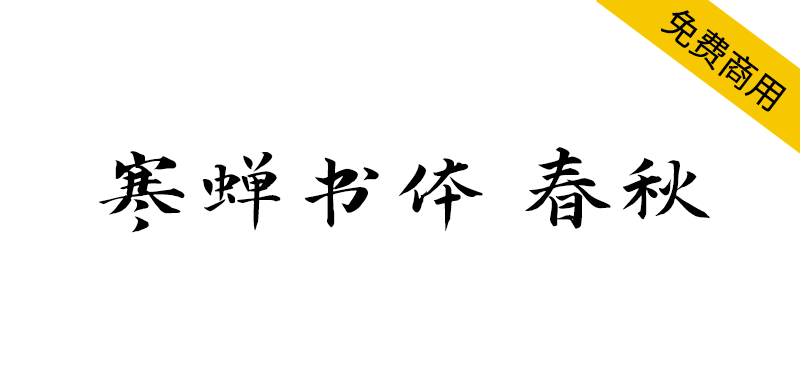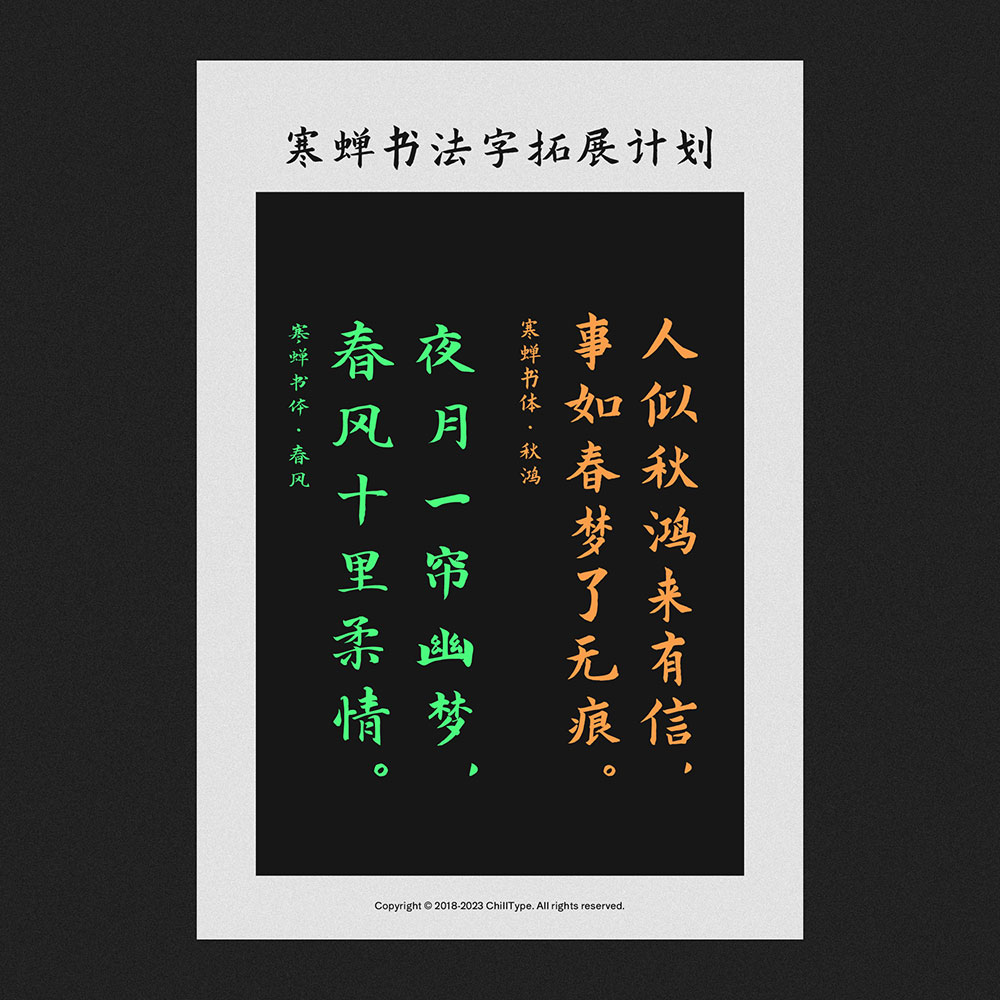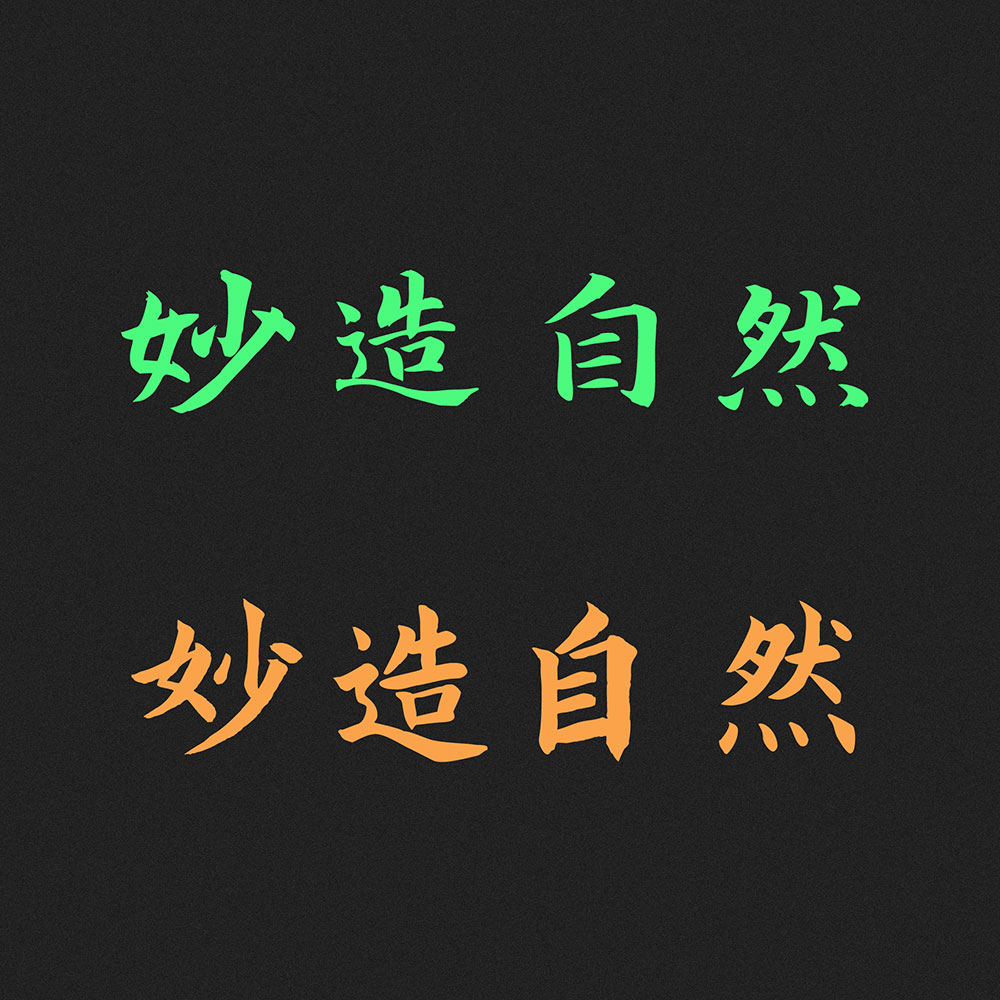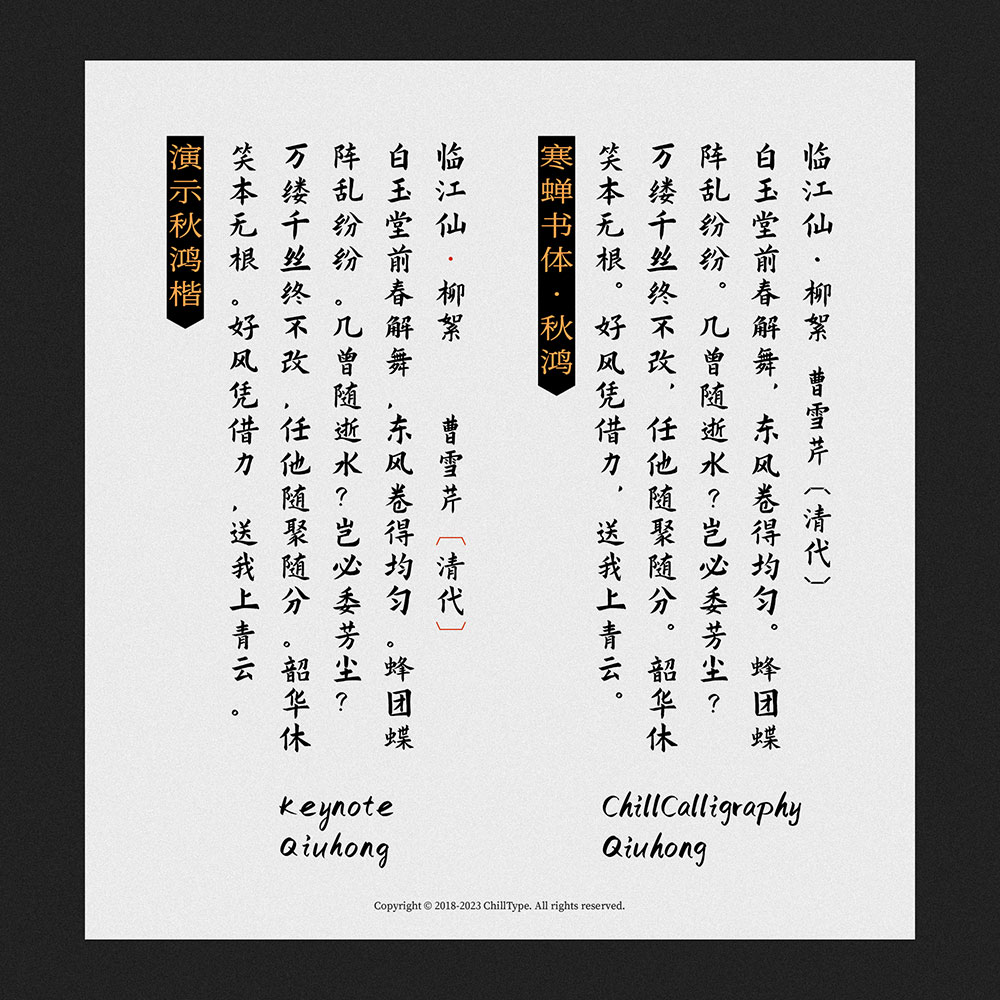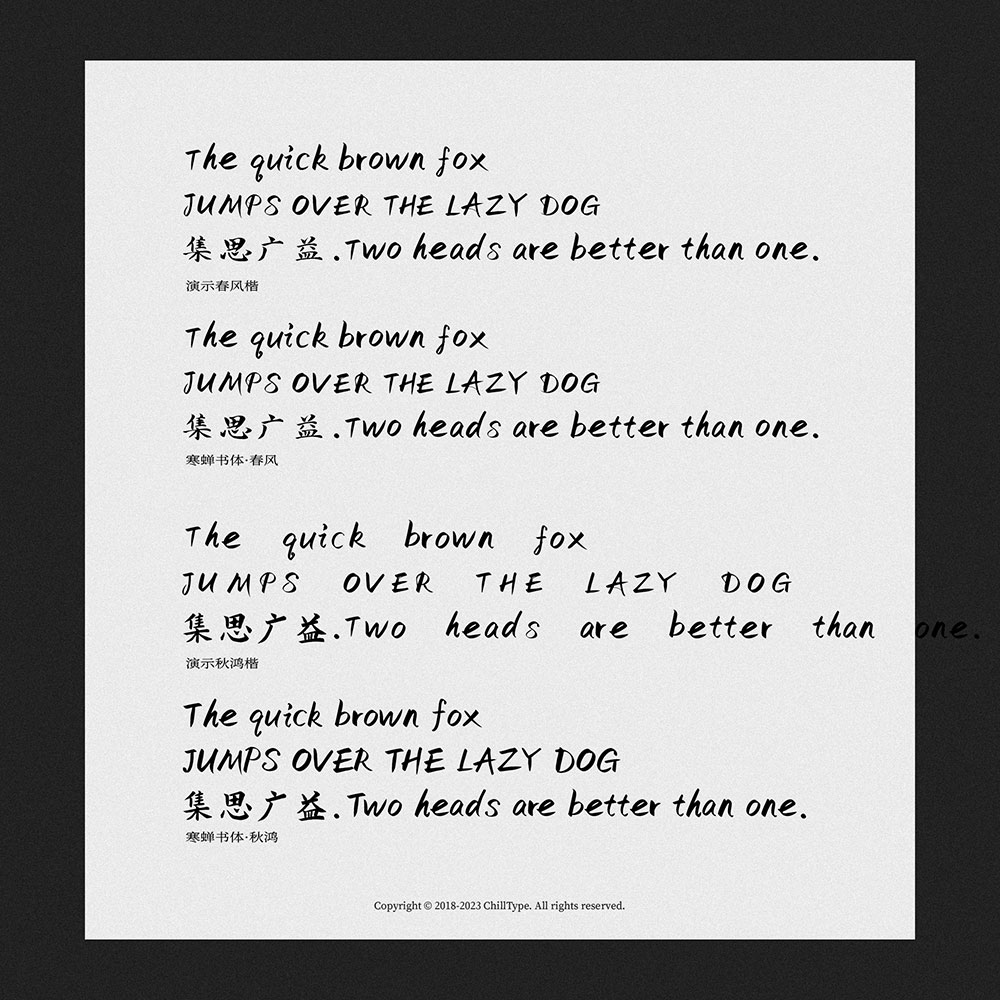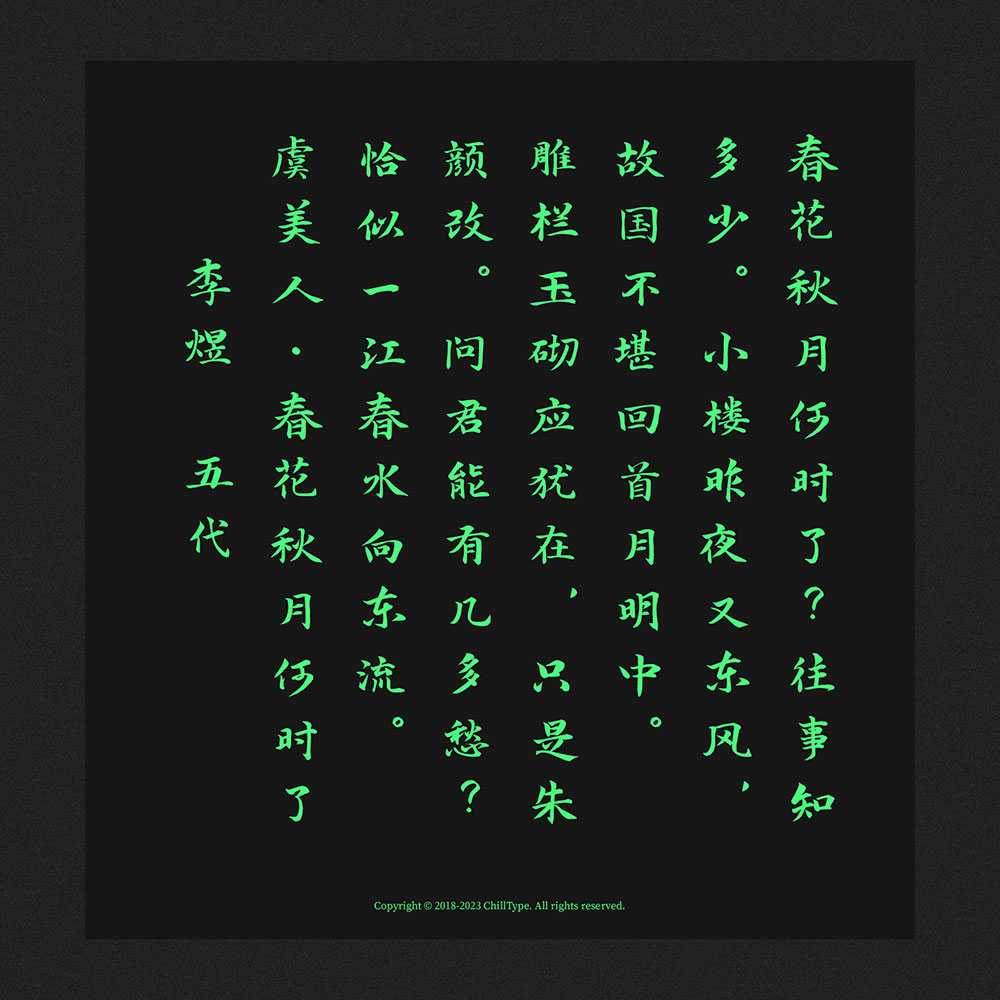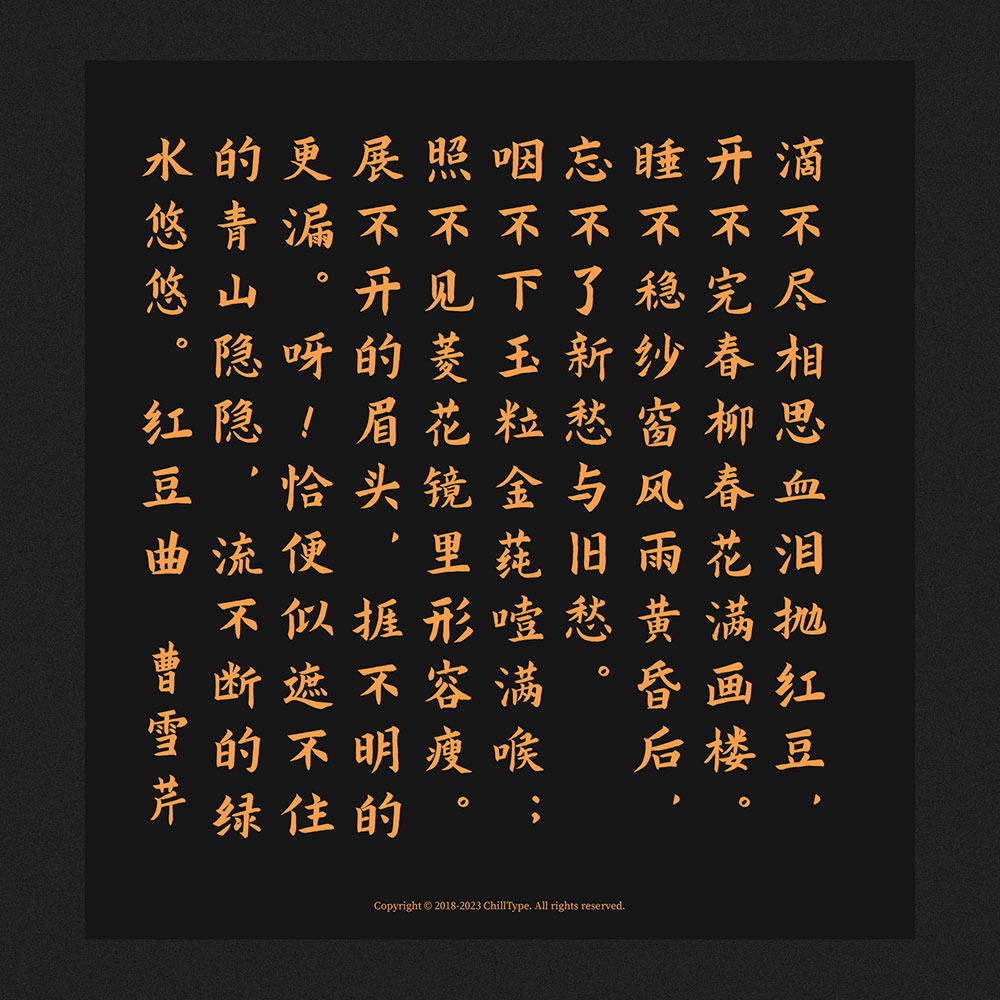
寒蝉书体_春秋是基于开源字体“演示春风楷、演示秋鸿楷”的拓展字形
春风 更新提要
调整西文字符及数字大小更加均衡。
调整部分字符忽高忽低的问题。
调整西文字偶距,优化横向排版。
优化竖向排版。
新增 啰 瞭 舖 三字补全一级规范通用字。
新设计的.notdef,补充一些标点符号。
秋鸿 更新提要
调整西文字符及数字大小更加均衡,去除连笔和文字风格更接近,调整粗细。
调整部分字符忽高忽低的问题。
调整西文字偶距,优化横向排版。
优化竖向排版。
新增 隹 啰 瞭 舖 啫 五字补全一级规范通用字。
新设计的.notdef,补充一些标点符号。